搜索玩具总动员的字体,你会得到一长串下载结果,而每一个看上去都稍微有点不对。这不是运气问题。玩具总动员的标志不是一种字体,而是两种,而大多数下载页面只给你其中一种的近似版本。
好消息是,另外那一半你可能早就合法地装在电脑里,只是自己不知道。
本文把两者分开,明确说出每一种你可以拿来做什么(大多数页面在这里含糊其辞),列出真正让人一眼认出「玩具总动员」的四个要素,并演示怎样不安装任何东西就做到。下面所有图片都来自 TextStudio 的玩具总动员字体生成器。
标志是两种字体,不是一种
「TOY」这个词,就是大家脑中那种粗厚圆润的字。它是为电影专门画的,从未作为字体发布过,所以任何地方都不存在合法的字体文件。
「STORY」这个词是红色色块里那个较小的词,而它是一款真正在售的字体:Gill Sans Ultra Bold。埃里克·吉尔于 1928 年为 Monotype 绘制了 Gill Sans 家族,Ultra Bold 是其中最粗的字重,也就是这里用的那一款。
这种拆分正好解释了下载后的失望。一个叫「玩具总动员字体」的文件,给你的是手绘那一半的仿制品,而另一半什么也没有,可让整个构图成立的恰恰是两者的搭配。
你是不是已经有了其中一半?
很有可能,而且在下载任何东西之前,这两分钟值得花。
「TOY」那一半从未发布,那有哪些仿制字体?
反复出现的名字是 Pizzadude 的 Agent Red 和 Agent Orange,以及 SF Slapstick Comic。它们在气质上很接近:粗重、圆润、略带歪斜的大写字母。
究竟是什么让它读起来像玩具总动员
这是下载页面跳过的部分,而它比字体本身更重要。四样东西在起作用:
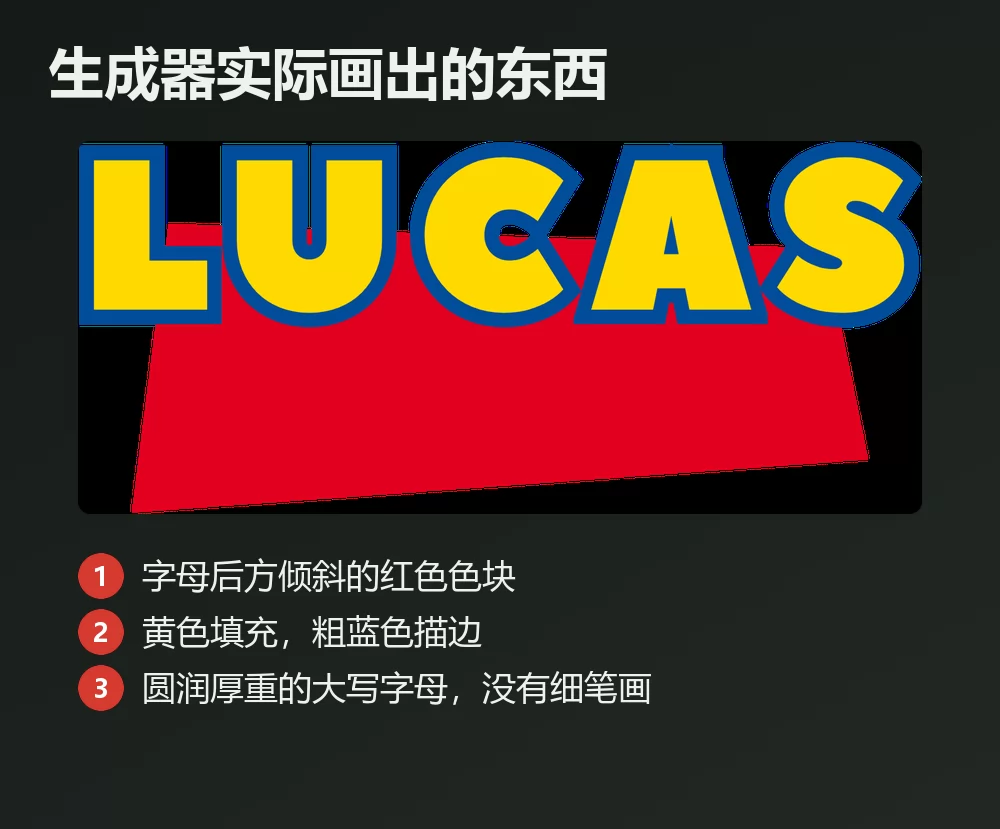
- 一块朝一侧倾斜的红色四边形,作为色块置于标题之后,而不是一个摆正的矩形。
- 标题朝相反方向倾斜,使两个角度彼此对冲。这种反向倾斜承载了整个构图几乎全部的活力。
- 黄色填充配厚重的蓝色描边,整个系列赖以运转的这对原色。
- 字母略微歪斜,每一个都有自己的小角度,像被孩子摆上去而不是排版排出来的。
把这四点做对,即使字体只是近似,风格也立得住。字体选得分毫不差却省掉反向倾斜,那就完全不像玩具总动员了。
关于上面这张图,有一点要老实说:生成器给你的是倾斜的红色色块、黄色填充和蓝色描边,而文字是摆正的。如果你想要原版那种反向倾斜和逐字不同的角度,就导出透明 PNG,自己旋转几度。这最后一步大约五秒钟,却是「接近」和「到位」之间的差别。
不安装任何字体也能做出这个风格
装一款字体只解决一半问题。它给不了描边、填充、倾斜的红色色块,也给不了逐字的角度,而这正是上面四点中的四点。手工做出来,意味着图层样式、一个形状图层,还要逐个旋转每个字母。
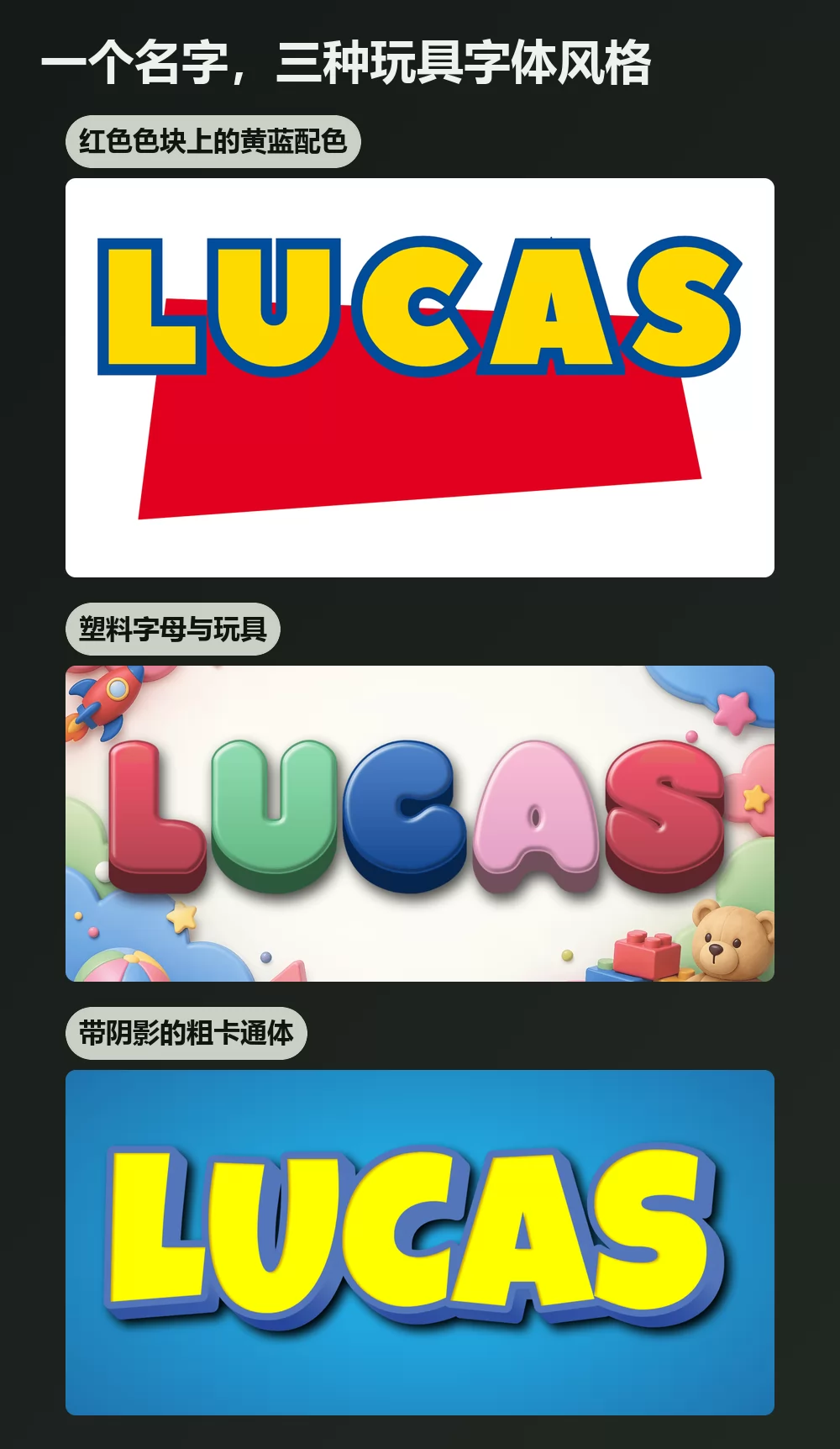
常见问题
玩具总动员标志用的是什么字体? 两种。「STORY」用的是 Gill Sans Ultra Bold,「TOY」是为电影绘制、从未作为字体发布的手绘字。
哪款免费字体最像玩具总动员的字母? 设计师最常用 Pizzadude 的 Agent Red 和 Agent Orange,还有 SF Slapstick Comic。它们都仅限个人使用,任何商业工作之前请先看条款。
玩具总动员标志用了哪些颜色? 红色色块上的黄色字母配蓝色描边。通篇都是明亮的原色,这在很大程度上解释了为什么这个风格一眼就能认出来。